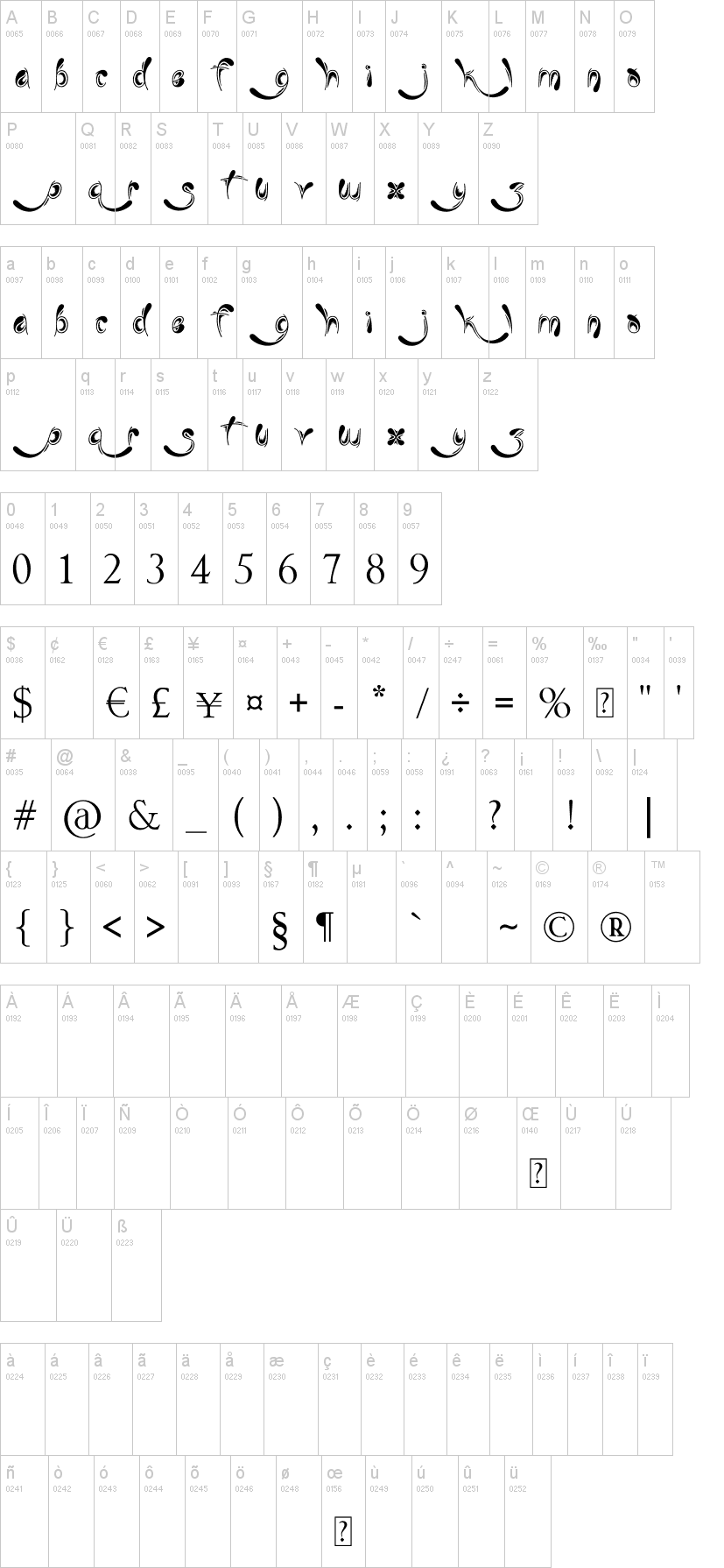
Naughty Nights
Naughty Nights(淘气之夜)是一款手写字体,它拥有一种活泼、欢乐的气氛,可以帮助你创造出独特的设计。它的字形充满活力,具有强烈的个性,可以为你的设计增添活泼的色彩。Naughty Nights字体可以用于海报、T恤、卡片等创意设计中,它的活泼、现代的风格可以更好地表达你的想法。
Naughty Nights是一款非常不错的手写艺术字体,具有很好的视觉感,适合于文化类的宣传设计、商业类品牌的广告和产品包装设计以及个性化文字排版等较多场景。
Naughty Nights字符映射图